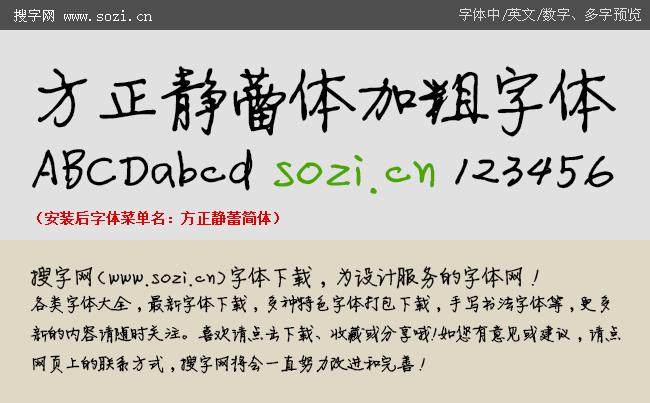
方正靜蕾體加粗字體
搜字網(wǎng)提供一款手寫風(fēng)格的手機(jī)中文字體方正靜蕾體加粗字體下載,方正靜蕾體是方正電子攜手徐靜蕾發(fā)布了其個(gè)人書法計(jì)算機(jī)字庫(kù)產(chǎn)品,字體骨骼清秀、遒勁有力,清冽而又優(yōu)雅、從容,令人賞心悅目。喜歡的朋友趕快下載吧。